Nama Font iPhone Beserta Cara Mengubah Ukurannya
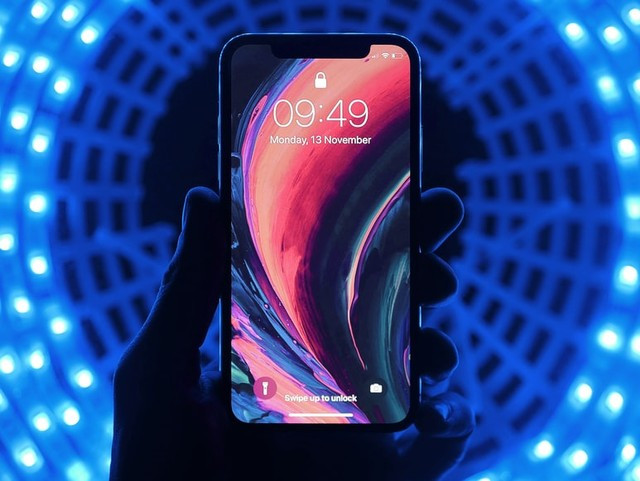
iPhone dikenal memiliki keunggulan dan keistimewaannya sendiri dibanding pesaingnya Android. Salah satu yang menjadi daya tarik banyak orang adalah tampilan dari font iPhone.
Selain menarik, fon iPhone menjadi salah satu ciri khas ponsel dan produk Apple lainnya. Huruf, angka, simbol khusus, dan tanda baca pada iPhone dinilai elegan dan berbeda dengan huruf bawaaan yang ada pada ponsel Android.
Meskipun sudah menjadi primadona, banyak orang yang belum tahu nama font iPhone. Lewat artikel ini, How To Tekno akan menjabarkan nama-nama fon yang dipakai dalam sistem iPhone.
Nama Font iPhone
Perusahaan Apple diketahui telah beberapa kali mengubah fon untuk sistem maupun fon interface mereka. Melansir laman Every mac, pada saat memproduksi iPhone 3G, Apple menggunakan fon Helvatica.
Tentunya, nama font iPhone tersebut sudah tidak asing lagi di telinga para pengguna perangkat elektronik. Fon Helvatica dibuat oleh Max Meidinger dan Eduard Horffman untuk sistem iOS.
Sebelum menjadi Helvatica, nama huruf tersebut adalah Neue Haas Grotesk. Nama Helvetica berasal dari bahasa Swiss yang memiliki arti tulisan. Huruf tersebut secara resmi digunakan oleh Apple untuk sistem OS X Yosemite, iOS 7, iOS 4, dan iOS 8.
Namun untuk sistem yang ada saat ini, Apple menggunakan jenis fon San Fransisco pada produk-produk terbarunya. Mengutip dari laman Developer Apple, San Fransisco adalah jenis fon Sans Serif yang terdiri dari SF Pro, SF Pro Rounded, SF Mono, SF Compact, dan SF Compact Rounded.
Fon SF Pro digunakan oleh Apple untuk produk iOS, MacOS, hingga tvOS. Sementara fon SF Compact adalah fon yang digunakan untuk Apple Watch. Artinya, saat ini seluruh produk dari Apple memakai fon San Fransisco tersebut.
Fon ini dirancang agar sesuai dengan visual UI milik Apple dan memberikan pengalaman membaca yang lebih jelas ke pengguna produk iPhone.